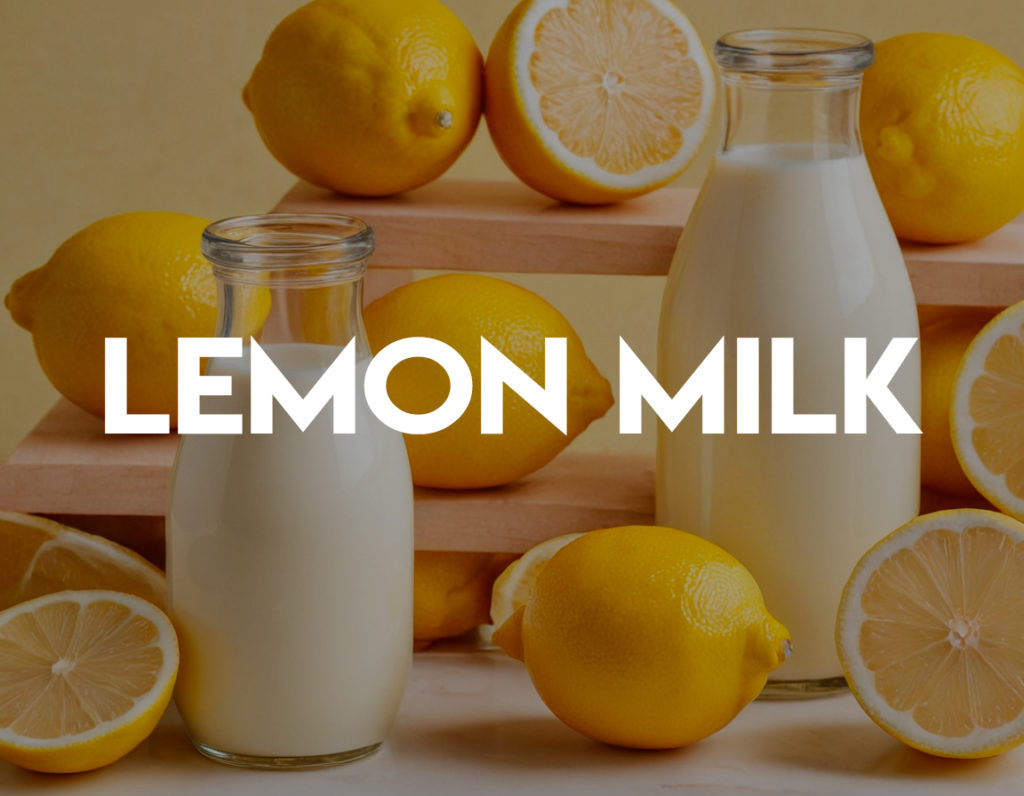
Геометрические формы, чистая структура и сбалансированный контраст штрихов делают этот кириллический шрифт универсальным инструментом для дизайнеров. Он отлично читается как в заголовках, так и в небольших текстах благодаря четкому рисунку букв. В комплекте вы получите полный набор начертаний (от легкого Light до жирного Bold) — скачать бесплатно можно сразу после установки.